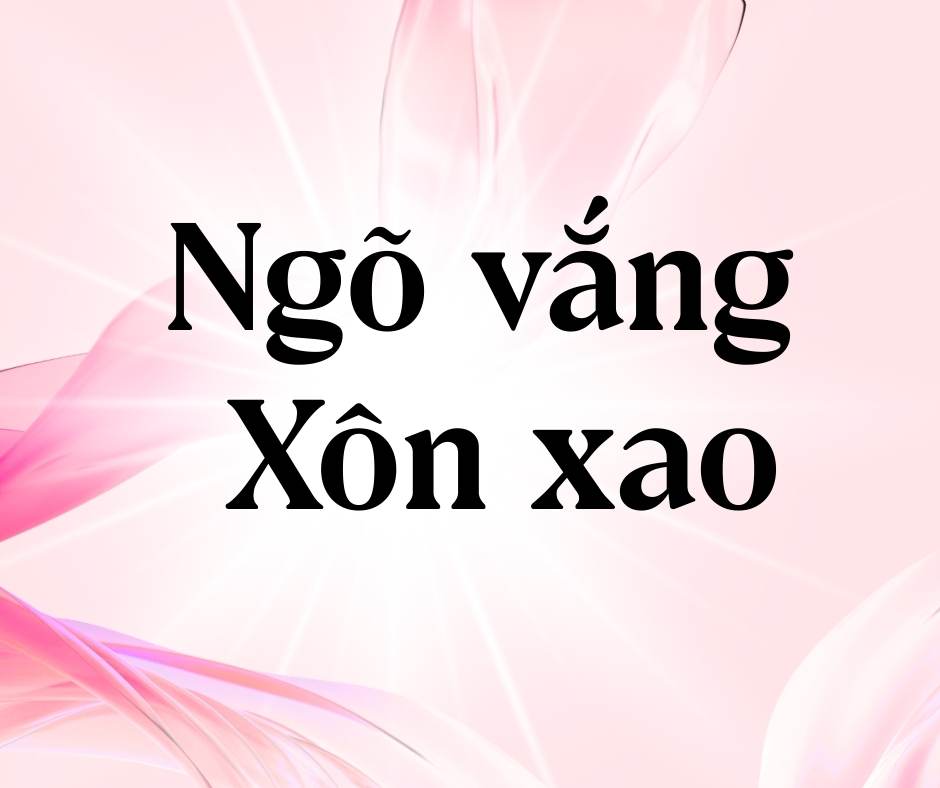
Bạn đang tìm kiếm một phông chữ mang đậm chất tạp chí cao cấp? Font Việt hóa VIP Exclusive Editorial chính là lựa chọn hoàn hảo. Với đường nét sang trọng, tinh tế và độ tương phản cao, bộ font này được thiết kế đặc biệt cho các ấn phẩm thời trang, nhận diện thương hiệu (branding), poster hay thư mời cao cấp. Bản Việt hóa VIP chuẩn chỉnh giúp bạn gõ tiếng Việt có dấu mượt mà, không lỗi typography. Khám phá và tải ngay Exclusive Editorial để nâng tầm dự án thiết kế của bạn trở nên chuyên nghiệp và cuốn hút hơn!
Tải 2 Font Việt hóa VIP Exclusive Editorial – Phông Chữ Sang Trọng Cho Thiết Kế Đẳng Cấp
Giới thiệu về Font Việt hóa VIP Exclusive Editorial
Trong thế giới thiết kế đồ họa, việc lựa chọn đúng phông chữ có thể quyết định sự thành bại của một tác phẩm. Nếu bạn đang theo đuổi phong cách sang trọng, thanh lịch và mang đậm hơi thở của các tạp chí thời trang hàng đầu thế giới, thì Font Việt hóa VIP Exclusive Editorial chính là “vũ khí” không thể thiếu trong bộ sưu tập của bạn. Đây là một trong những bộ font chữ đẹp được săn đón nhất hiện nay nhờ vẻ đẹp vượt thời gian và tính ứng dụng cực cao.
Đặc điểm nổi bật của Exclusive Editorial
Exclusive Editorial mang trong mình DNA của phong cách thiết kế tạp chí (editorial design). Điểm nhấn của bộ font này nằm ở:
Đường nét tinh tế, độ tương phản ấn tượng: Sự kết hợp hoàn hảo giữa những nét thanh mảnh và nét đậm dứt khoát tạo ra một nhịp điệu thị giác vô cùng bắt mắt. Điều này giúp dòng chữ của bạn nổi bật nhưng không hề có cảm giác thô cứng.
Chất lượng Việt hóa VIP: Khác với các bản Việt hóa trôi nổi trên mạng, phiên bản Font Việt hóa VIP Exclusive Editorial được chăm chút tỉ mỉ từng dấu câu (dấu ngã, dấu hỏi, dấu nặng…) để đảm bảo sự cân đối hoàn hảo. Kerning (khoảng cách giữa các chữ cái) được tinh chỉnh lại cho phù hợp với đặc thù của tiếng Việt, giúp bạn không cần tốn thời gian căn chỉnh thủ công khi thiết kế.
Ứng dụng tuyệt vời trong thiết kế
Với vẻ đẹp kiêu kỳ và sang trọng, Font chữ tạp chí Exclusive Editorial là sự lựa chọn số 1 cho các dự án đòi hỏi tính thẩm mỹ cao cấp:
Nhận diện thương hiệu (Branding): Rất phù hợp cho logo, bao bì sản phẩm của các thương hiệu thời trang, mỹ phẩm, trang sức hay spa cao cấp.
Thiết kế ấn phẩm truyền thông: Poster, banner quảng cáo, cover tạp chí, lookbook thời trang sẽ trở nên thu hút và chuyên nghiệp hơn rất nhiều.
Thiết kế sự kiện: Sử dụng làm font chữ thiệp cưới, thư mời sự kiện VIP hay menu nhà hàng hạng sang.
Kết luận
Sở hữu một phông chữ sang trọng và hỗ trợ tiếng Việt hoàn hảo như Font Việt hóa VIP Exclusive Editorial sẽ giúp bạn tiết kiệm thời gian thiết kế mà vẫn đạt được hiệu ứng thị giác tối đa. Đừng bỏ lỡ cơ hội bổ sung “tuyệt tác” typography này vào thư viện của bạn. Hãy tải ngay hôm nay để biến những ý tưởng thiết kế của bạn thành những tác phẩm nghệ thuật thực thụ!